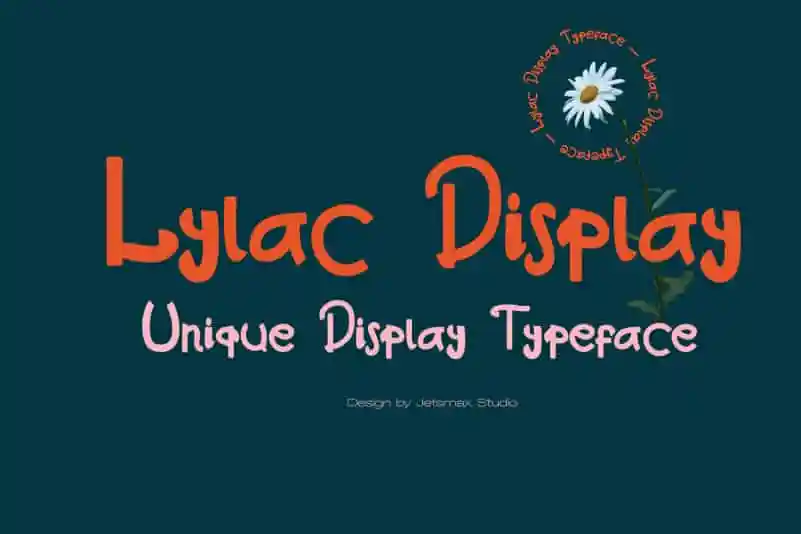
Lylac Display Font – Download Grátis
A fonte Lylac Display é uma criação elegante inspirada no belo florescente das primaveras. Embalada com um toque poético que transmite uma sensação de delicadeza e frescor, essa fonte decorativa oferece um tom cuidadosamente carreado em cada letra, garantindo um visual sofisticado para qualquer projeto gráfico. Seu designer, jetsmax, certificou-se de trazer uma beleza única à Lylac Display Font através da harmonização cuidadosa e detalhada de cada sílaba, tornando-a perfeita para o design editorial ou a criação de materiais publicitários que buscam um toque especial. Uma fonte dessas permite que qualquer projeto possa se destacar com uma aparência única e sofisticada.
Designer: jetsmax